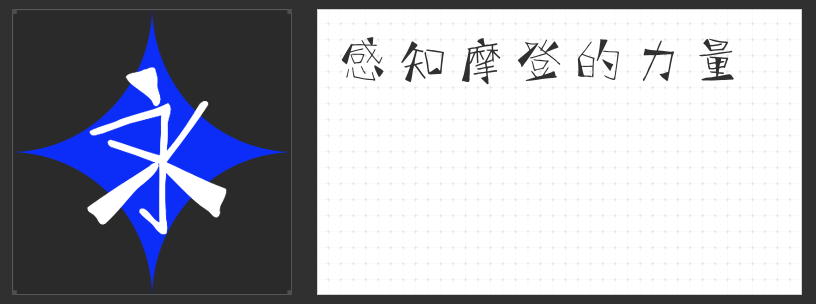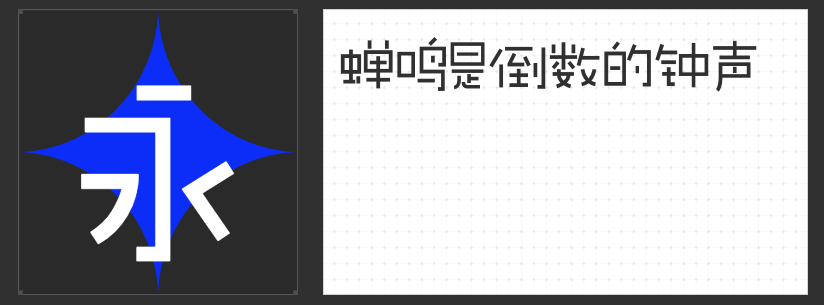
四款魅力字库字体,点亮短视频视觉新体验
在短视频内容创作中,字体的选择往往能成为点睛之笔,为作品注入独特的个性与氛围。今天,我们特别推荐四款各具特色的字库字体,它们不仅具备出色的视觉表现力,更能为短视频增添别样的艺术魅力。
一、字恋狂漫野 鸣风
这款字体以手写感为灵魂,直线笔画中蕴含着张弛有度的结构美学。其布白空间通透,字型大小错落有致,仿佛自然呼吸般富有节奏感。简洁的笔画设计去除了冗余的钩与弯,以直线组合变化营造出均匀的灰度,让版面在保持清晰的同时,又不失活泼与灵动。
二、字恋狂澄空 拂风
同样以手写感为基础,这款字体在字型上展现出上松下紧的独特韵味,重心略低却更显稳健。字面随字型结构灵活变化,字间距安排得当,组合起来如同音乐般富有韵律。笔画设计简洁流畅,弧线与直线的融合恰到好处,部分折笔处的平直切角处理,更添一份利落与轻快。
这款草书字体连笔流连,笔画流畅恣意,仿佛带着诗意与温暖的气息。中宫更大、笔画更粗的设计,不仅增强了字体的辨识度,更提升了其实用性。在短视频中,它能轻松营造出一种文艺而又不失大气的氛围。
这款字体以粗细有致的线条和干净利落的点划,呈现出一种简约摩登的形象。看似随意的笔画,实则疏密有致,韵律感十足。它特别适用于二次元、动漫、旅行等类别的视频场景,能为作品增添一份时尚与活力。
这四款字体各具特色,无论是追求手写感的自然与灵动,还是偏爱草书的诗意与温暖,亦或是钟情于简约摩登的时尚气息,都能在其中找到心仪之选。让它们成为你短视频创作中的得力助手,共同点亮视觉新体验!